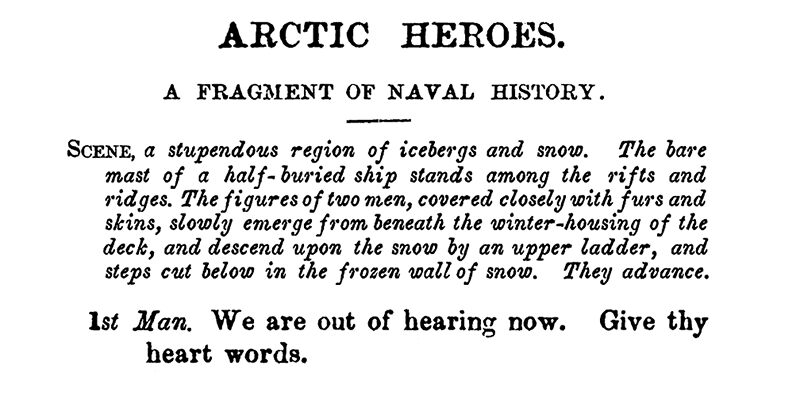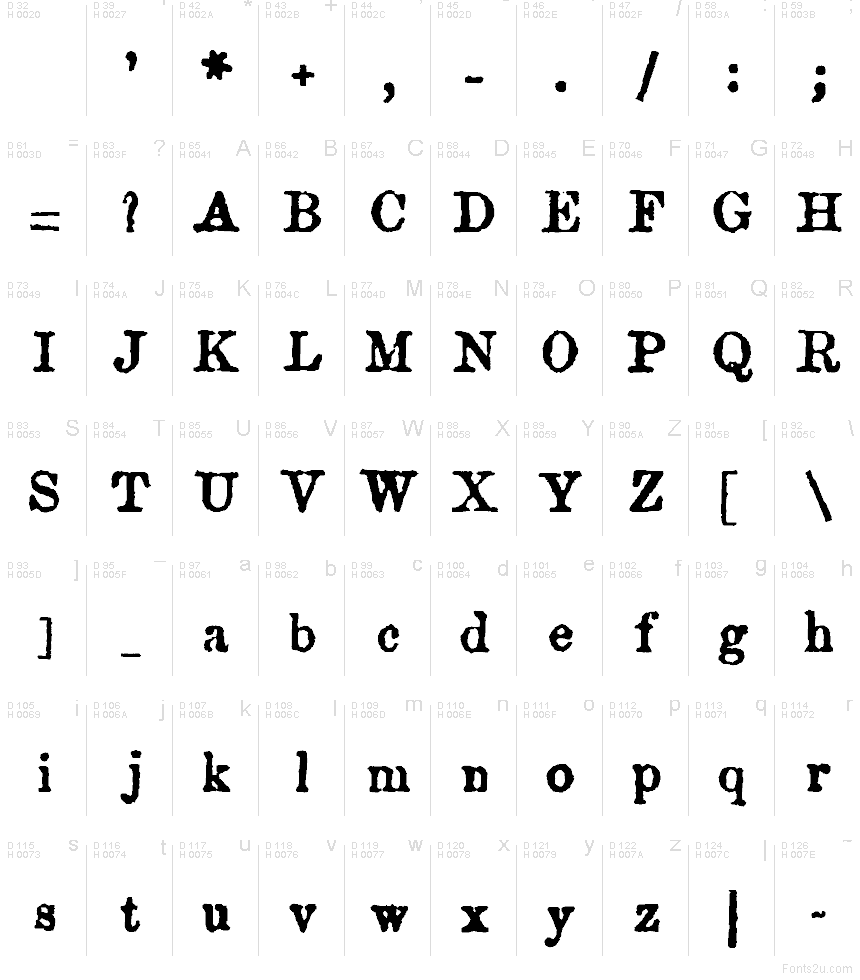
Household Words je bezplatné, záměrně opotřebované display písmo, které má syrovou autoritu starých dřevěných typů. Písmena vypadají jako z těžkého tisku a jsou lehce ošlehaná, s roztřepenými okraji, vyštípanými křivkami a tlustými blokovými tvary. To dodává abecedě atmosféru éry novinového tisku, působí dojmem ručního otisku, a nikoliv sterilního digitálního dokončení.
Tato drsná textura se hodí pro nadpisy plakátů, obálky knih, vývěsní štíty, redakční titulky a obaly, kde má bezplatný font nést historickou váhu, aniž by působil příliš křehce. Použijte jej, když chcete, aby krátké řádky a názvy působily jako vyražené, zvětralé a trochu výrazné, zejména v designech, které čerpají z viktoriánské typografie a drsných tiskovin.
Font Household Words je obnovou dávno zaniklého typu písma z 19. století, který vytvořil Gary Stephens.